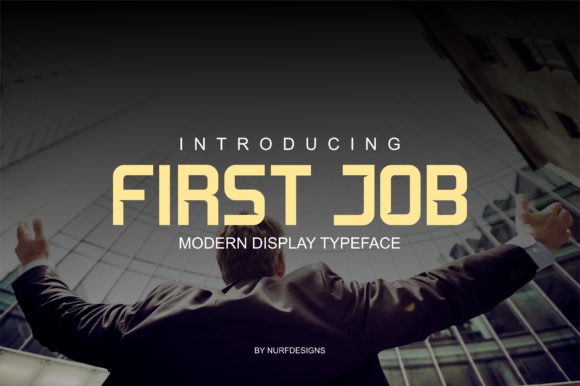
First Job Typeface – Download Grátis
A fonte ‘First Job Typeface’ é uma criação elegante e moderna, ideal para qualquer projeto que exige profissionalismo e estilo. Seja para criar anúncios impactantes ou manuais de instruções detalhados, esta font oferece precisão e conforto ao trabalhar com letras do início ao fim. Desenvolvida pelo designer nurfdesigns, a ‘First Job Typeface’ foi criada pensando em uma comunicação rápida e eficaz. Com um design minimalista que ressalta o conteúdo principal de seu texto, é perfeita para quem busca transmitir uma mensagem clara e assertiva. Com sua ampla gama de opções e variedade interessante de pesos e itálicos, essa fonte permite personalizar seus materiais em graus diversos. Seja você um designer gráfico atento aos detalhes ou alguém com mais experiência na área que busca algo simples e funcional, a ‘First Job Typeface’ pode ajudar a tornar seu trabalho de criação mais eficiente e atraente. Instale-a agora e desfrute da combinação perfeita entre estilo e praticidade. Com a fonte ‘First Job Typeface’, sua próxima tarefa no escritório ou na sala de reuniões ficará ainda melhor!